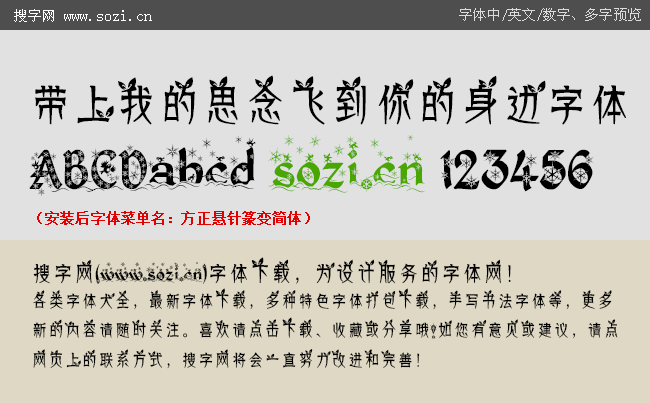
帶上我的思念飛到你的身邊字體
搜字網(wǎng)給大家提供一款帶上我的思念飛到你的身邊手機(jī)中文字體下載。這款手機(jī)字體是在方正懸針篆變簡(jiǎn)體筆畫(huà)間插入了可愛(ài)的雪花等卡通圖案。方正懸針篆變字體意在保留篆書(shū)韻味,同時(shí)將隸書(shū)與楷書(shū)筆畫(huà)特征熔于一爐,實(shí)為三種書(shū)體的統(tǒng)一。將傳統(tǒng)書(shū)法藝術(shù)與現(xiàn)代形式語(yǔ)匯融合,追求裝飾性及藝術(shù)美感,端莊秀美、開(kāi)張疏朗,雍容大氣、復(fù)古卻易讀。加入了卡通圖案后又增添了趣味性,特別適合喜歡手機(jī)字體個(gè)性一些的朋友在手機(jī)上安裝使用。